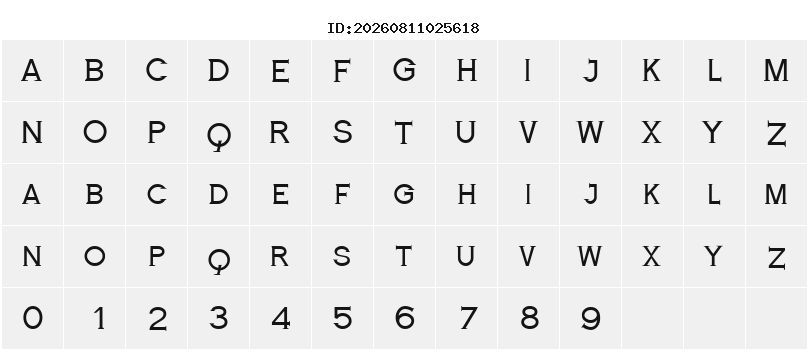
• Font Name: Royal Serif
• Designer: Tipografia Vittoria
• Description: Serif Royal è un font serif con maiuscolo/maiuscoletto dalle linee molto classiche, le grazie ricordano molto il cosiddetto "stile romano". Questo font è adatto a grafiche di stampo classico quali biglietti da visita e carta da lettere per liberi professionisti od aziende di tipo tradizionale. Autore del font è Tipografia Vittoria con sede a Firenze, tipografia e centro stampa artigianale, sito web: http://www.tipografiavittoria.com
About Royal Serif.ttf
Royal Serif.ttf is a modern, elegant sans-serif font designed for ultimate readability and visual harmony. Perfect for branding, headlines, web design, and print materials.